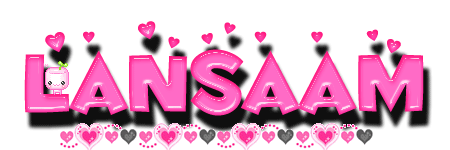
รับทำอักษรเยลลี่นะจ๊ะ
ได้แล้วค่ะ :22:
โอ้  :25: :25:  +1 จ้า ไม่นึกว่าจะเร็วเยี่ยงนี้
แก้ให้ค่ะนึกว่าตัว I ซะอีก
:45: ไม่ต้องแก้ละนะครับ สวยละ
ตัวใสๆ วุ้นๆ ราดด้วยน้ำหวานครับ
ได้แล้วค่ะ
ผิดตรงไหนบอกด้วยนะคะ
แล้วจะเอาไอ้ดึกดึ๋ยนี่ไปทำอะไร ยังนึกไม่ออก  :09:
เอาไปใส่เว็บค่ะ
รึจะเอาไปแต่งที่ไหนก็ได้ค่ะ
ก่อนที่จะตั้งกระจู๋ก็เอาชื่อเราขึ้นก่อนแล้วค่อยพิมพ์เนื้อหาค่ะ
จะได้เด่นแท้แน่ชัดว่าเราโพสนะคะ (ตัวหนูคิดยังงี้นะ :25:)